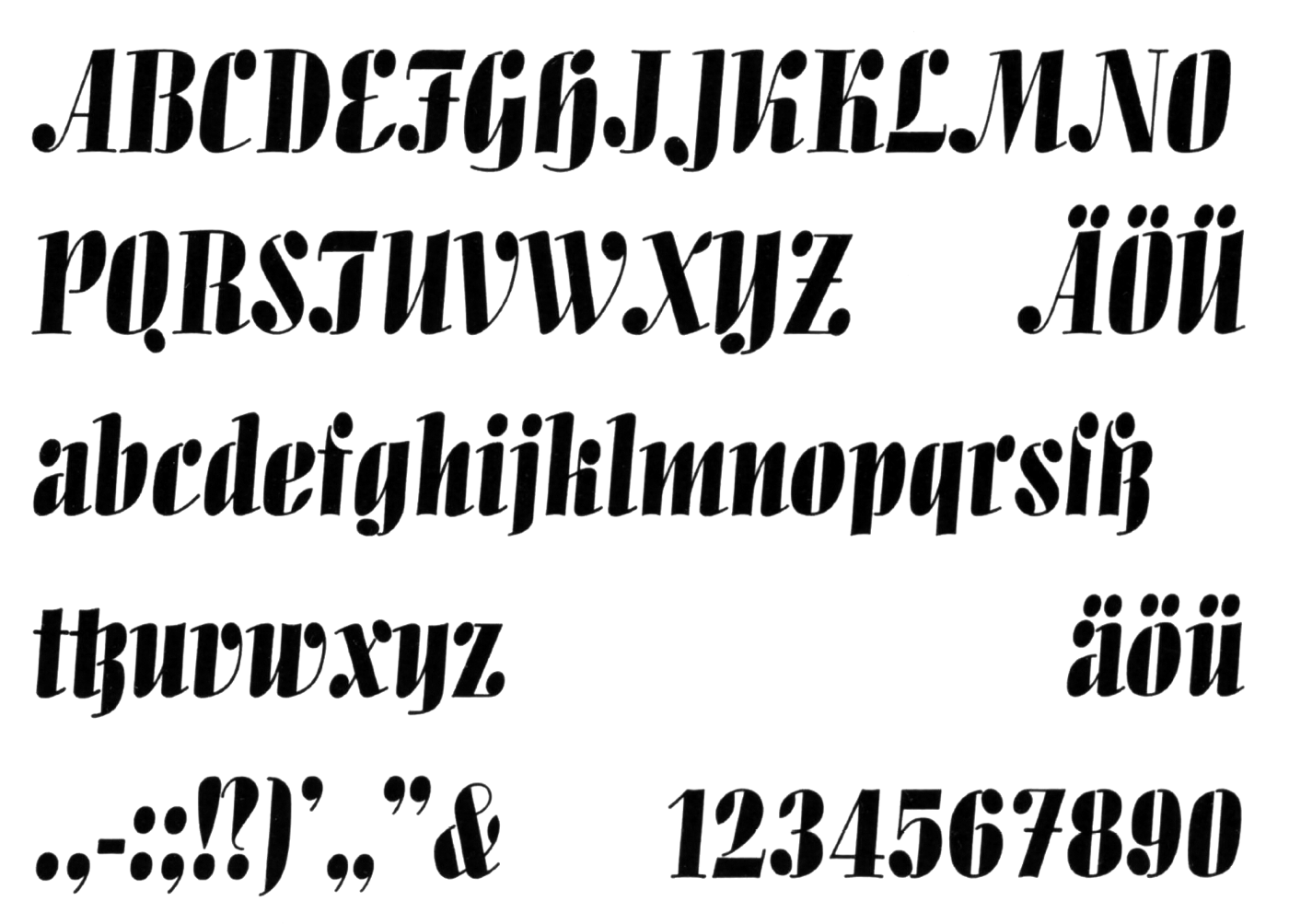
• 1936
• Serifen:
• serif
• Antiqua dekorativ
Die Allegro ist eine dekorative Antiqua-Schrift von Hans Bohn und erschien in den 1930er-Jahren bei Ludwig & Mayer. Die Gießerei stellte die Allegro der Schrift »Die Schlanke« als Schaugrößenschrift zur Seite.
Eine Digitalisierung mit westeuropäischer Belegung gibt es von Bitstream. Zeichenformen und Zeichensatz entsprechen aber nicht vollständig der Bleisatzversion.